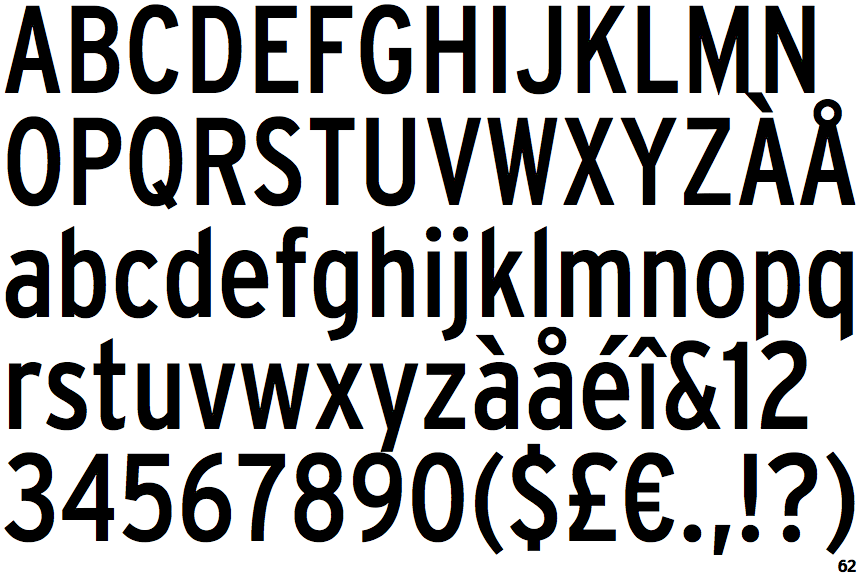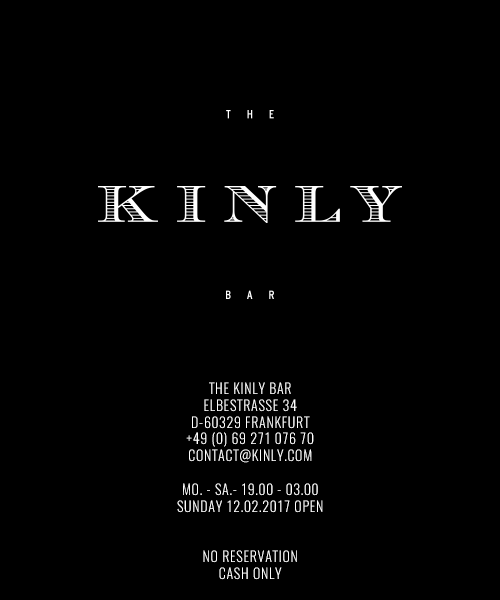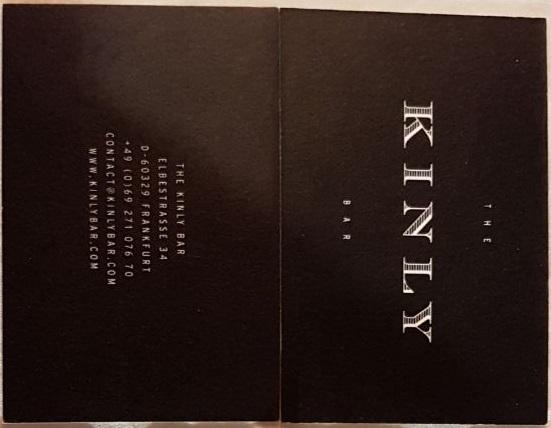
[Suche]: Schriftarten von beigefügtem Foto (Visitenkarte)
ich bin auf der Suche nach kostenlosen Schriftarten, welche den beiden auf der Visitenkarte (siehe Anhang) verwendeten möglichst nahe kommen und serifenlos sind. Leider weiß ich über die Schriften sonst nichts (soll eine Überraschung werden), würde mich aber trotzdem riesig freuen, wenn mir jemand weiterhelfen könnte. Danke schonmal!
Die Bildqualität ist nicht besonders überragend, ich rate deshalb zuerst die Streiflingsschrift:
Typeface:	Chevalier
Designer:	E. A. Neukomm
Year:		1946
Copyright:	Haas
Publishers:	Monotype Imaging and Linotype
Alternates:	Maurice SM, Chevara SM
No lower-case characters.
Die Grotesk würde ich an Hand der Ziffern als eine FHWA-Series, FHWA steht für Federal Highway Administration. Das ist/war also die Schilderschrift der Gringos auf deren „Bundesautobahnen“.
Eine Digitalisierung von Tobias Frere-Jones für Font-Bureau ist die Interstate:
Hier mal die Condensed ... http://www.identifont.com/show?2TMP
Eine Version von Typodermic gibt es hier unter dem Namen Expressway:
Leider hat die freie Overpass keine Condensed Schnitte.
Typeface:	Overpass
Publisher:	Redhat
Hier noch was aus der Mottenkiste mit Condensed:
Typeface: RoadGeek
Es ist dem nach die B-Serie ... also die FHWA B-Serie? Meine Unterlagen zeigen da noch eine AllCaps mit dem Namen Lane ABCDE, dabei aber auch der Hinweis, dass diese wegen Urheberrechtsverletzungen von Dafont entfernt wurde ... Ende der Durchsage ... *PIEEEEP*
"Chevalier Stripes" passt.
Hier ein besseres Beispiel – bringt mich aber für die Schriftart auch nicht weiter.
die Schilderschrift der Gringos auf deren „Bundesautobahnen“.
N.b. die wird für praktisch alle Verkehrsschilder und Wegweiser und somit für alle öffentlichen Straßenkategorien in allen 🇺‍🇸 Zuständigkeiten (Bund, Länder, Kreise, Kommunen) verwendet. Und ja, es gibt Roadgeek-Digitalisierungen für Series B, C, D, E, EEM, EM und F.
Roadgeek 2014 Series B
"Chevalier Stripes" passt.
Hier ein besseres Beispiel – bringt mich aber für die Schriftart auch nicht weiter.
Das ist aber eine andere Schrift als in dem Anderen Beispiel! *schwör* Das kann aber so ziemlich alles sein ... gesichtslos! Vielleicht eine Alternate Gothic 3? Da muss eine viel höhere Auflösung her.
Typeface:	Chevalier
Designer:	E. A. Neukomm
Year:		1946
Copyright:	Haas
Publishers:	Monotype Imaging and Linotype
Alternates:	Maurice SM, Chevara SM
No lower-case characters.